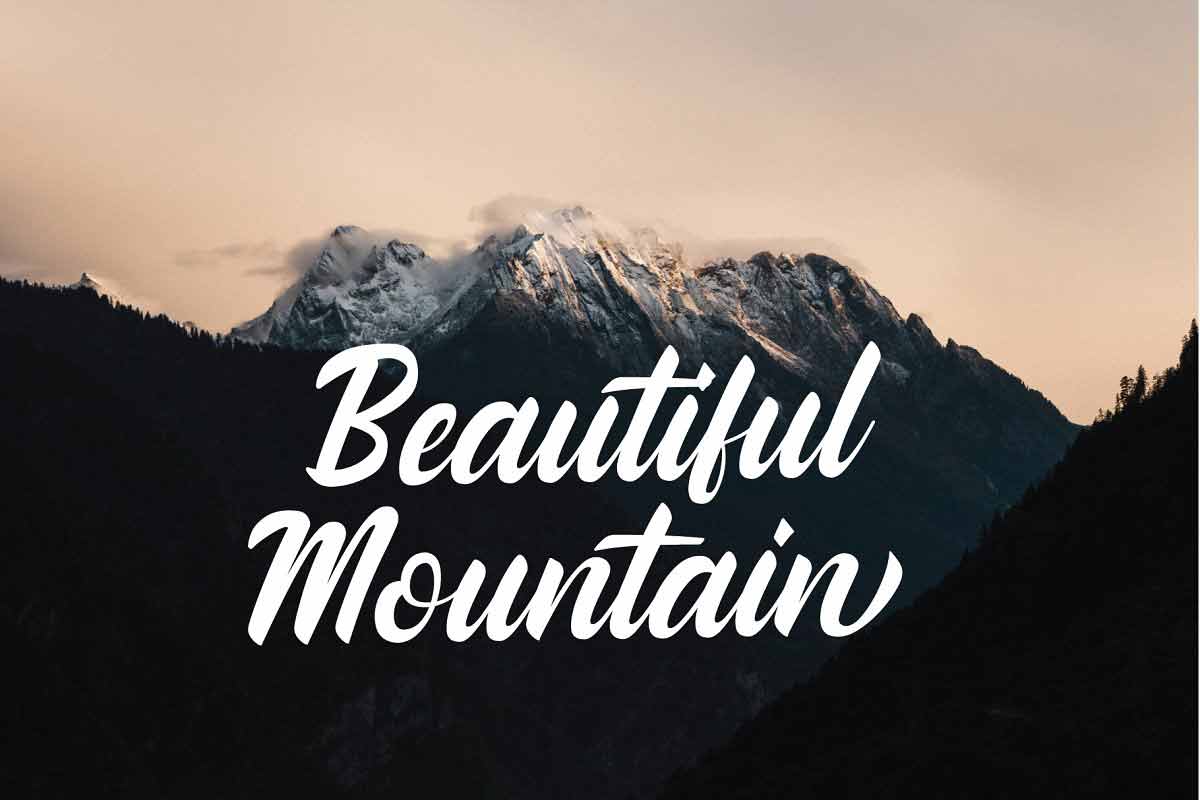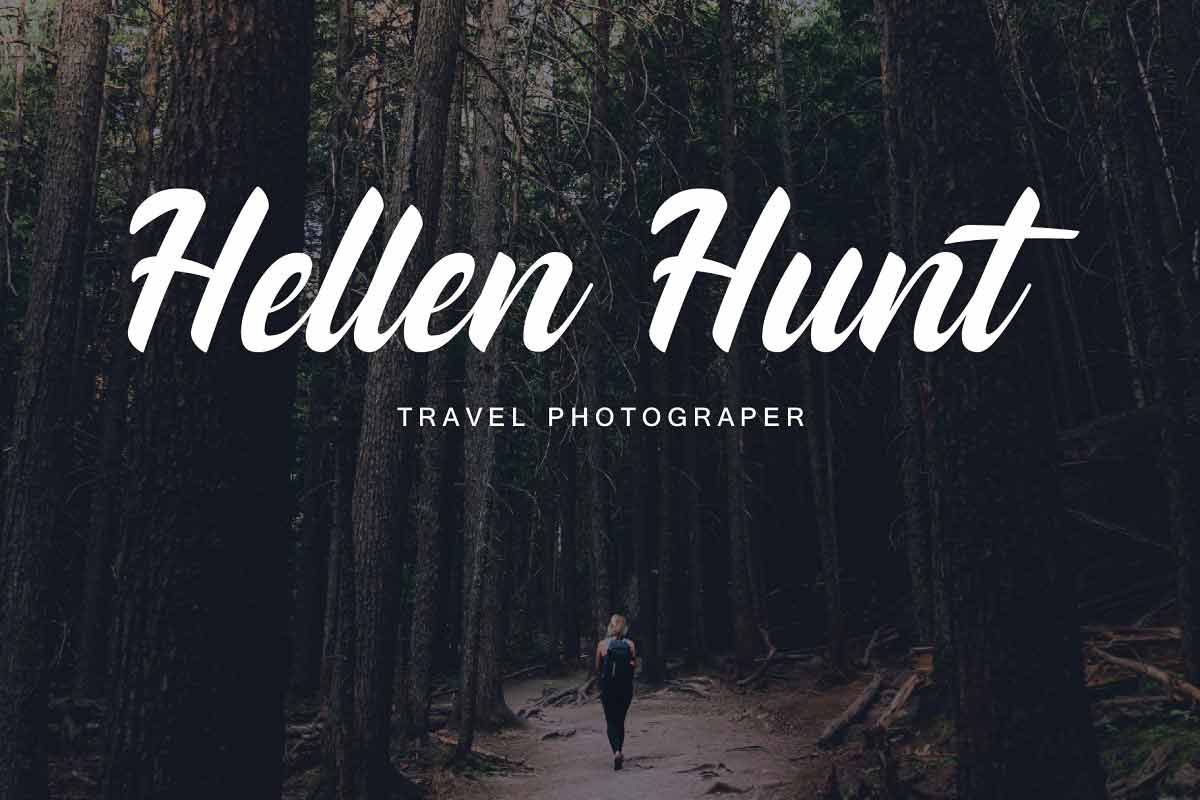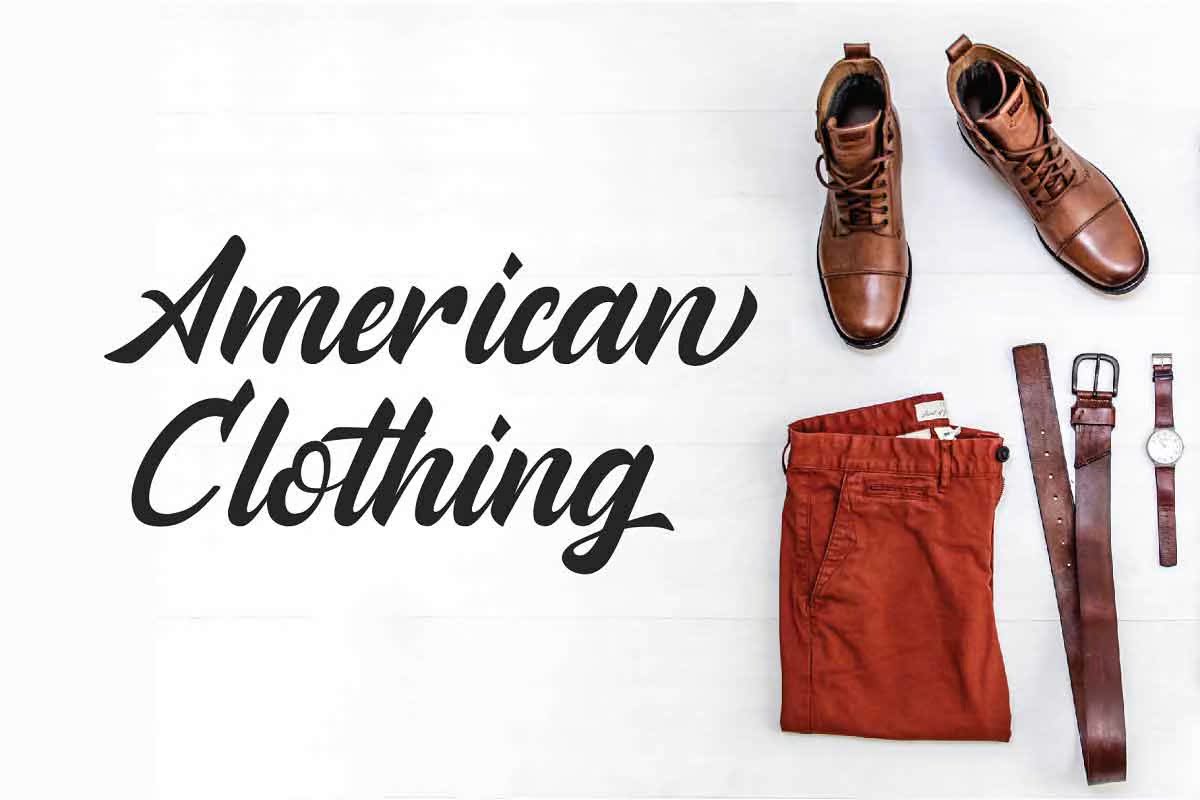
你好!简介GanamazingScriptFont,它是FreeDemoandAllanScriptFont。它是一个很好的ScriptFont字符,它可以为您的任何项目提供强大的支持。但是,它非常适合户外项目,另一方面,这个字体对您的所有项目都很好,包括名片、商品、传单、徽标、t恤等等。这个令人敬畏的自由字体已经准备好用于格式文件,但您只能使用具有个人许可证的网络类型。您可以通过购买PremiumVersion来获取更多。